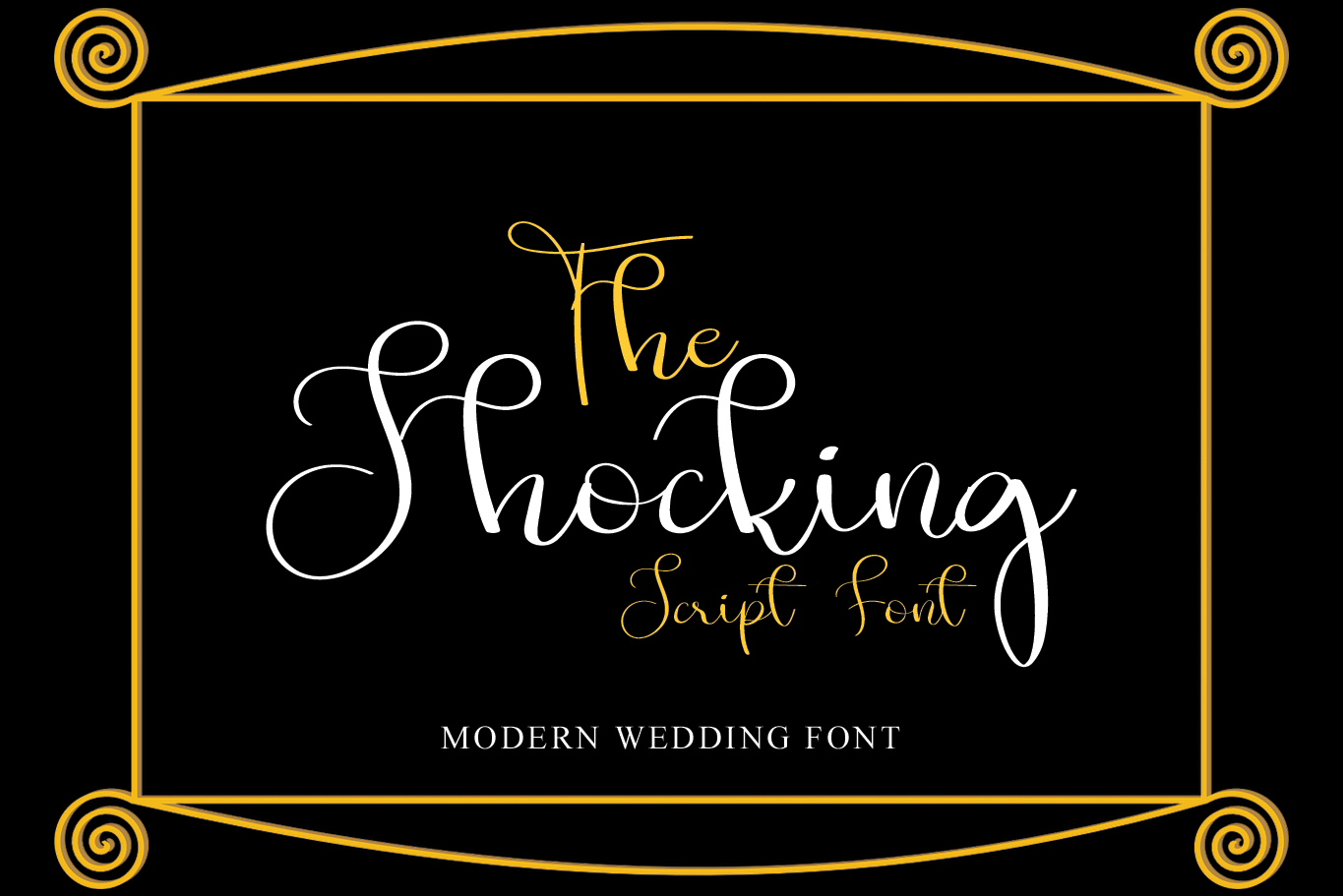
Esta é uma fonte tipográfica chamada The Shocking Font, que se destaca pela sua elegância e refinamento. Ideal para criar designes sofisticados, esta fonte moderna atende a um amplo espectro de aplicações, desde logotipos e identidades corporativas até cartões de visita, embalagens, anúncios de casamentos, publicações nas redes sociais e muito mais. É perfeita para aqueles que procuram uma fonte elegante e moderna para seus projetos gráficos. Com The Shocking Font, você pode criar designs incríveis que expressam tanto classe quanto atualidade. Este é um verdadeiro tesouro do mundo dos recursos gráficos de alta qualidade.